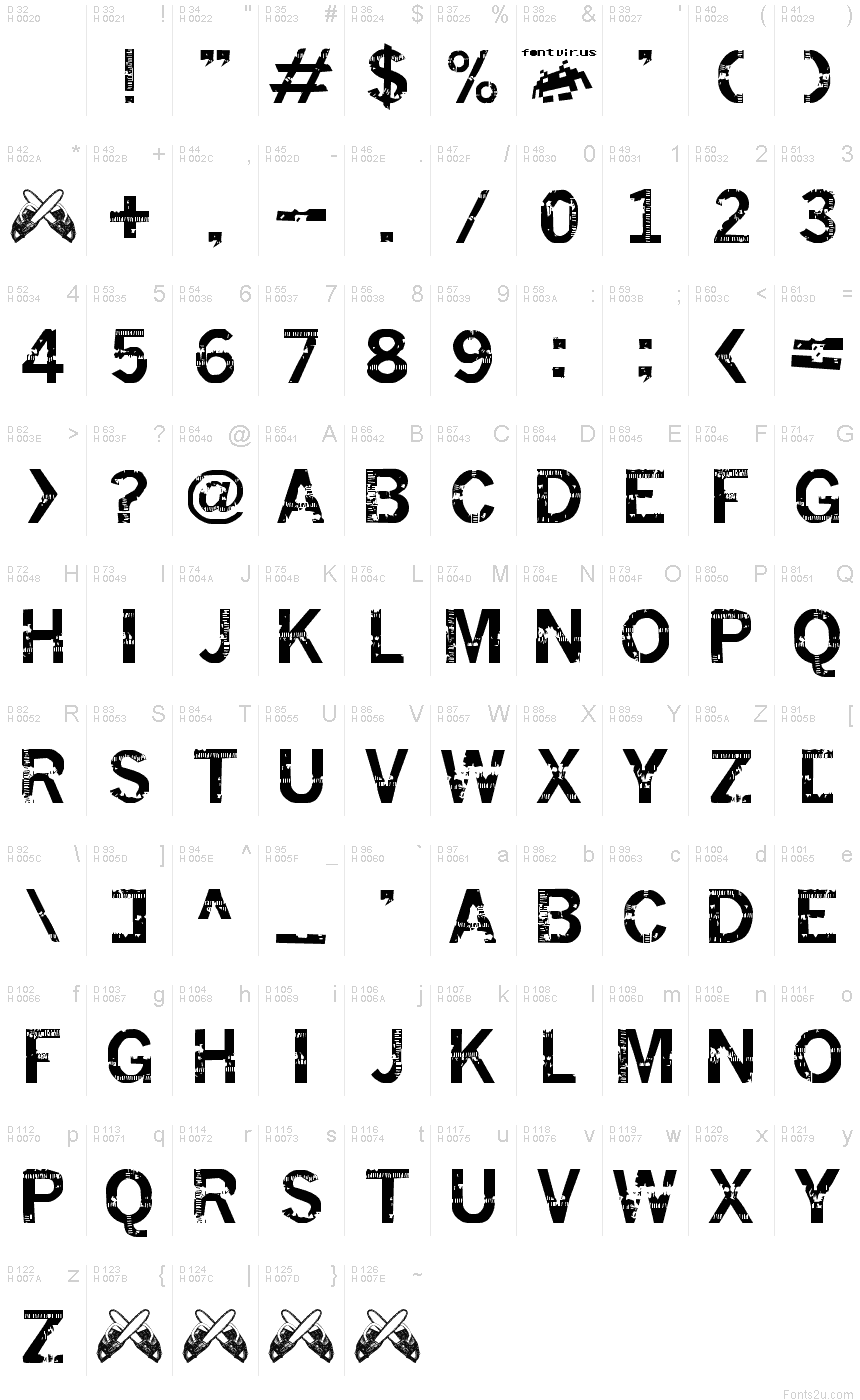
Insomnesia від Xero Harrison — це безкоштовний шрифт із ефектом ерозії, що передає атмосферу міських плакатів та афіш. Великі літери мають грубі злами, зазубрини та нерівні фрагменти, що створює враження, ніби їх відірвали від стін або пошкодили погодні умови, тоді як важкі силуети зберігають сміливий і різкий характер літер.
Це робить його природним вибором для концертних флаєрів, горор-заголовків, стрітвір-графіки, обкладинок зінів та «пошарпаного» брендингу, де звичайний чистий шрифт виглядав би надто охайно. Будучи безкоштовним шрифтом, він найкраще підходить для коротких заголовків, титрів та великих монограм, адже візерунок пошкоджень тут є головним голосом дизайну.